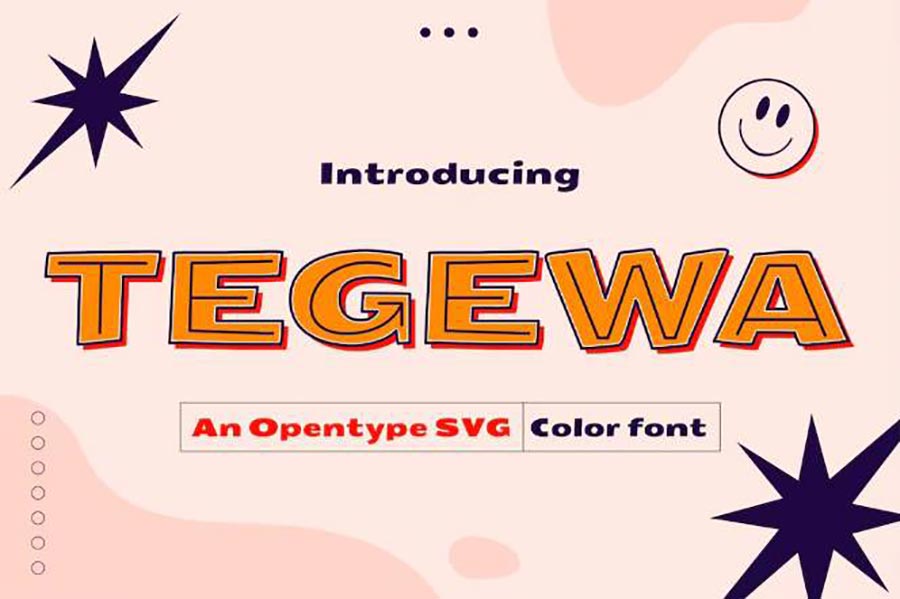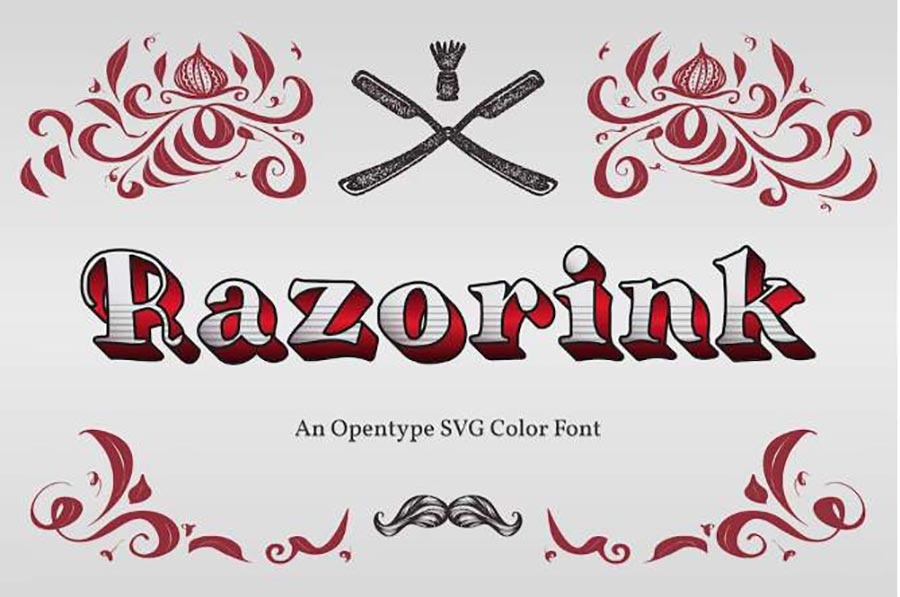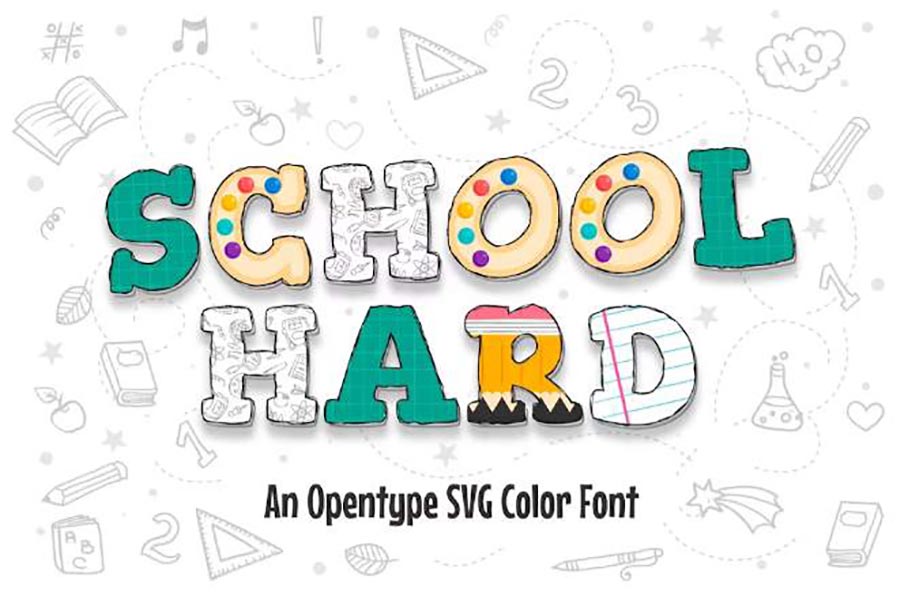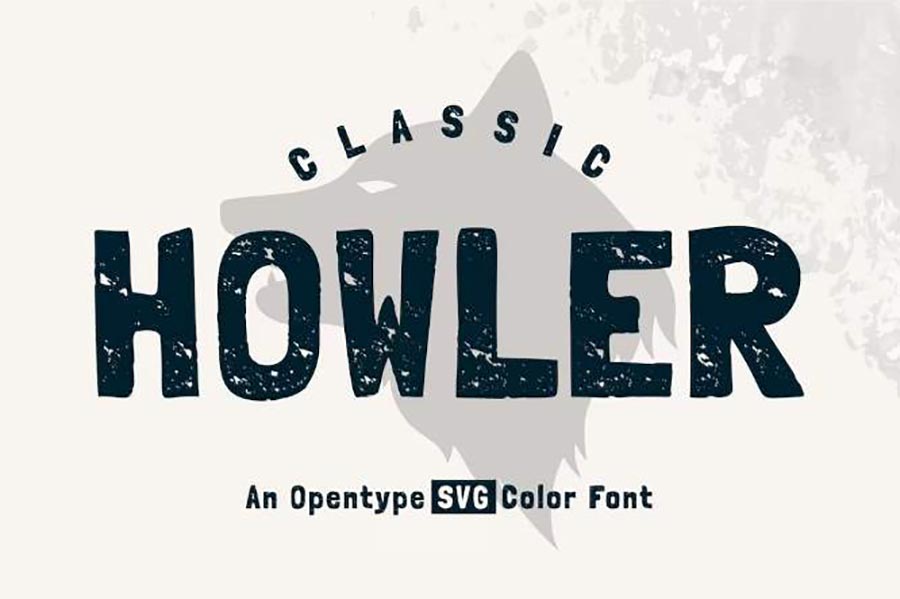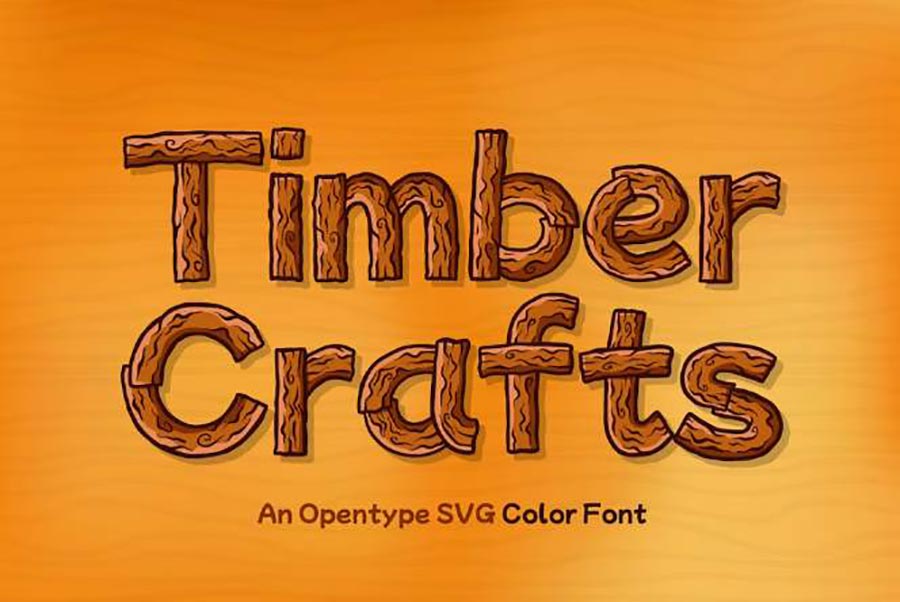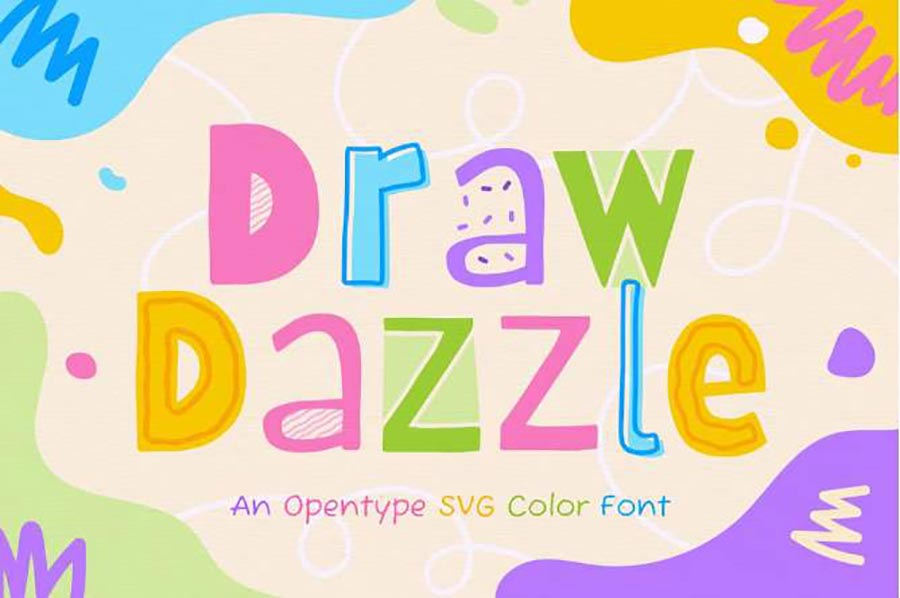
Trong thế giới thiết kế đồ họa, việc chọn lựa font chữ phù hợp là một yếu tố quan trọng để tạo nên những sản phẩm ấn tượng. Nếu bạn là một designer đang tìm kiếm những kiểu chữ sáng tạo và độc đáo, bộ Fonts Drawing miễn phí từ Sadesign.vn sẽ là sự lựa chọn lý tưởng. Với những font chữ mang đậm phong cách vẽ tay, bộ fonts này không chỉ giúp bạn thể hiện sự sáng tạo mà còn mang lại cảm hứng mới cho mọi dự án thiết kế. Hãy cùng tìm hiểu cách tải và sử dụng bộ Fonts Drawing này để nâng cao chất lượng thiết kế của bạn.
Fonts Drawing Là Gì?
Fonts Drawing là một bộ sưu tập các kiểu chữ được thiết kế với phong cách vẽ tay, mang lại cảm giác tự nhiên, độc đáo và nghệ thuật. Những font chữ này thường có đường nét mềm mại, linh hoạt, giống như những nét vẽ phác thảo thủ công, tạo ra sự gần gũi và cá tính riêng biệt. Chúng rất thích hợp cho các dự án thiết kế yêu cầu sự tinh tế và sáng tạo, từ logo, poster, thiệp mời, đến các thiết kế quảng cáo, bao bì và nhiều hình thức thiết kế khác. Với Fonts Drawing, bạn sẽ có cơ hội làm mới các thiết kế của mình bằng những kiểu chữ độc đáo, mang lại cảm hứng mới lạ cho các dự án sáng tạo.
Ứng Dụng Bộ Fonts Drawing Trong Thiết Kế:
Bộ Fonts Drawing có thể áp dụng vào rất nhiều loại hình thiết kế khác nhau. Dưới đây là một số ứng dụng phổ biến:
1. Thiết Kế Logo: Sử dụng fonts vẽ tay để tạo ra những logo độc đáo, mang đậm phong cách cá nhân, giúp thương hiệu của bạn nổi bật.
2. Thiết Kế Thiệp Mời: Với các nét vẽ tay mềm mại, bạn có thể tạo ra những thiệp mời cưới, thiệp Valentine, thiệp sinh nhật đầy lãng mạn và sáng tạo.
3. Quảng Cáo và Poster: Tạo ra các poster quảng cáo ấn tượng, các chiến dịch truyền thông thu hút người xem bằng những font chữ đặc biệt, nổi bật.
4. Thiết Kế Bao Bì: Bộ Fonts Drawing rất phù hợp để tạo ra những bao bì sản phẩm có sự tinh tế và sáng tạo, giúp sản phẩm của bạn nổi bật trên kệ hàng.
5. Nội Dung Mạng Xã Hội: Sử dụng fonts này để tạo ra những bài đăng trên mạng xã hội, các câu quote đầy cảm hứng, hay các bức ảnh mang đậm dấu ấn cá nhân.
Lợi Ích Khi Sử Dụng Fonts Drawing Miễn Phí Từ Sadesign.vn: